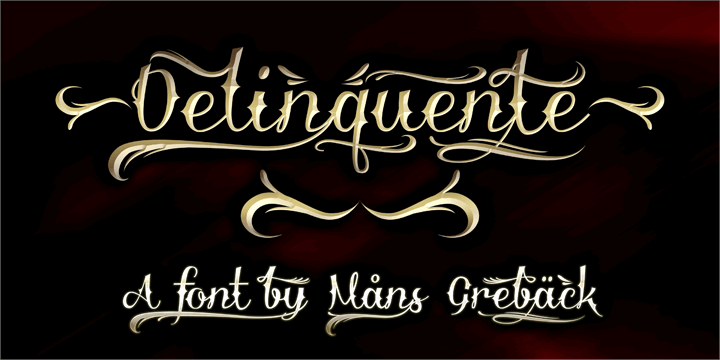
A fonte Delinquente é um script elegante criado pelo designer Hamilton, perfeito para quem busca uma fonte com estilo único para trabalhos comerciais ou publicidade. Com linhas finas e detalhes elaborados, Delinquente oferece o charme necessário para dar um toque diferenciado a qualquer layout gráfico. Esta font é especialmente adequada para uso em nomes de empresa, logotipos, materiais de marketing digital ou qualquer outro aplicativo que exija um design cuidadosamente pensado. Para obter mais informações e comprar uma licença comercial da Delinquente font, visite: http://www.mansgreback.com/delinquente. Se você está procurando por uma nova adição à sua paleta de fontes para trabalhos comerciais, não perca tempo – a Delinquente é definitivamente algo que você não pode deixar de ver.